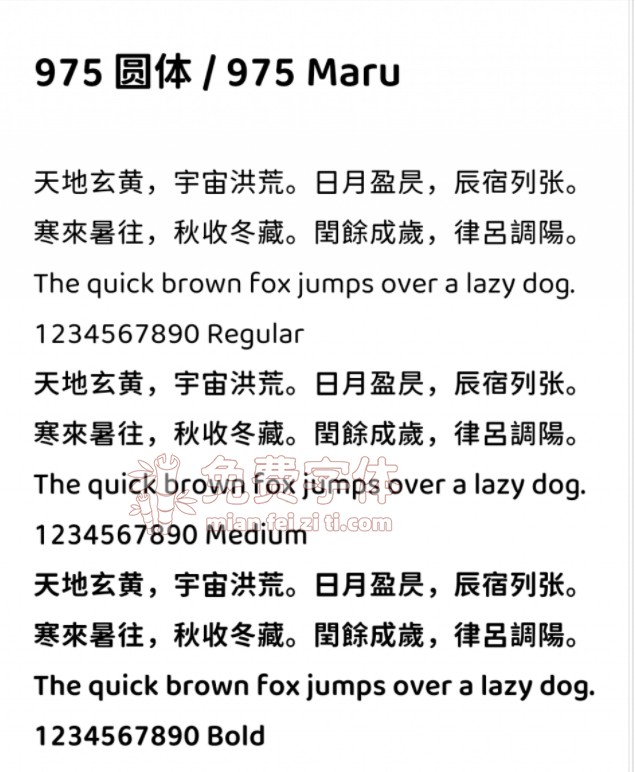
975圆体:基于思源黑体/狮尾圆体的缩小字面中文字体字体资讯
975圆体一款基于思源黑体/狮尾圆体的中文字体。在狮尾圆体的基础上调整。在保持原有字符宽度的同时,缩小字面至97.5%,并做少许加粗,使其更适合手机屏幕阅读。西文搭配经过调整处理的Baloo 2字体。暂时只有简体中文(SC)版本。
这不是一个专业的字体文件。已知问题:在中文和西文合并的过程中,思源黑体原有的OpenType特性丢失,会导致纵向排版特性无法正常体现。